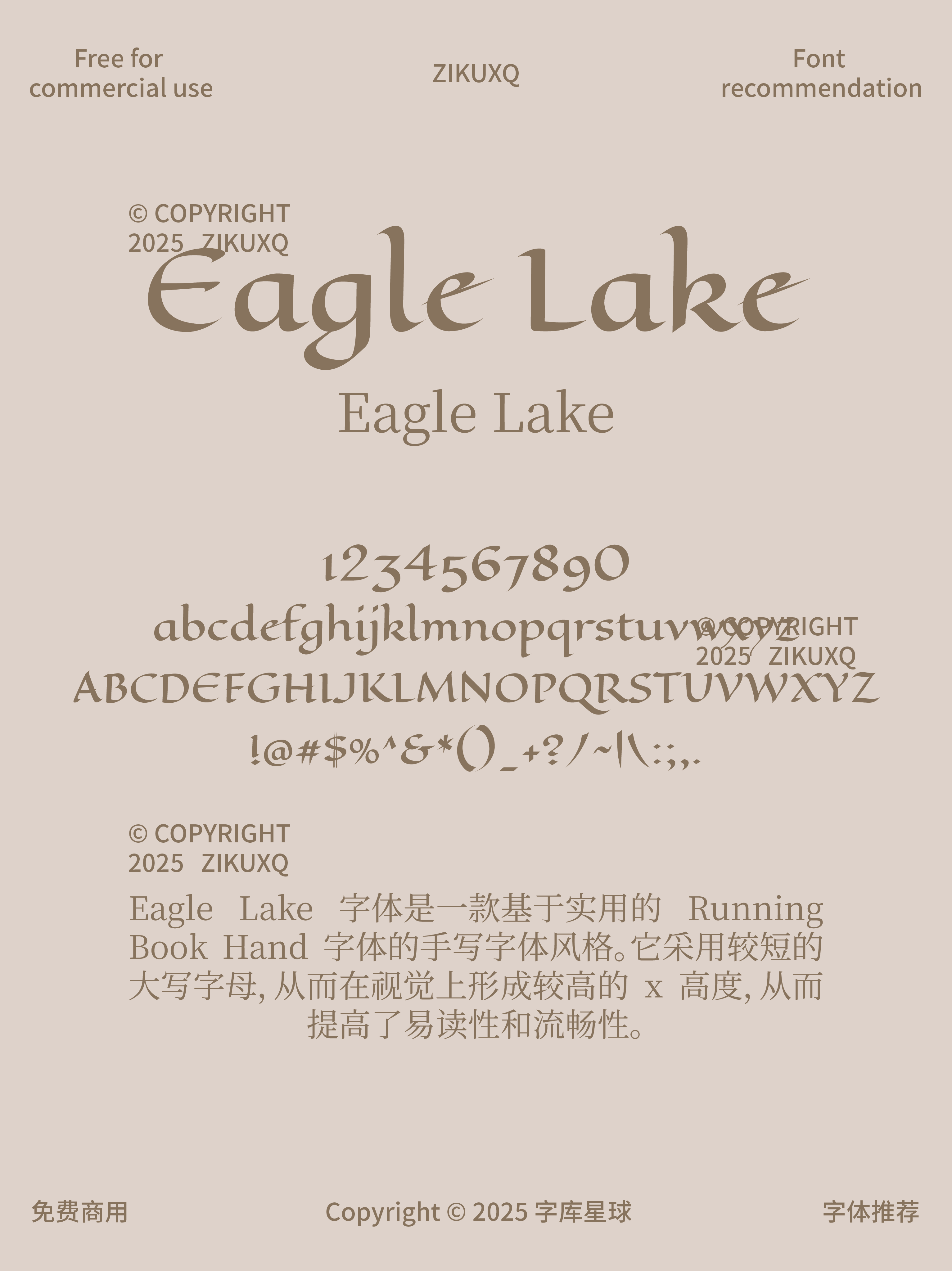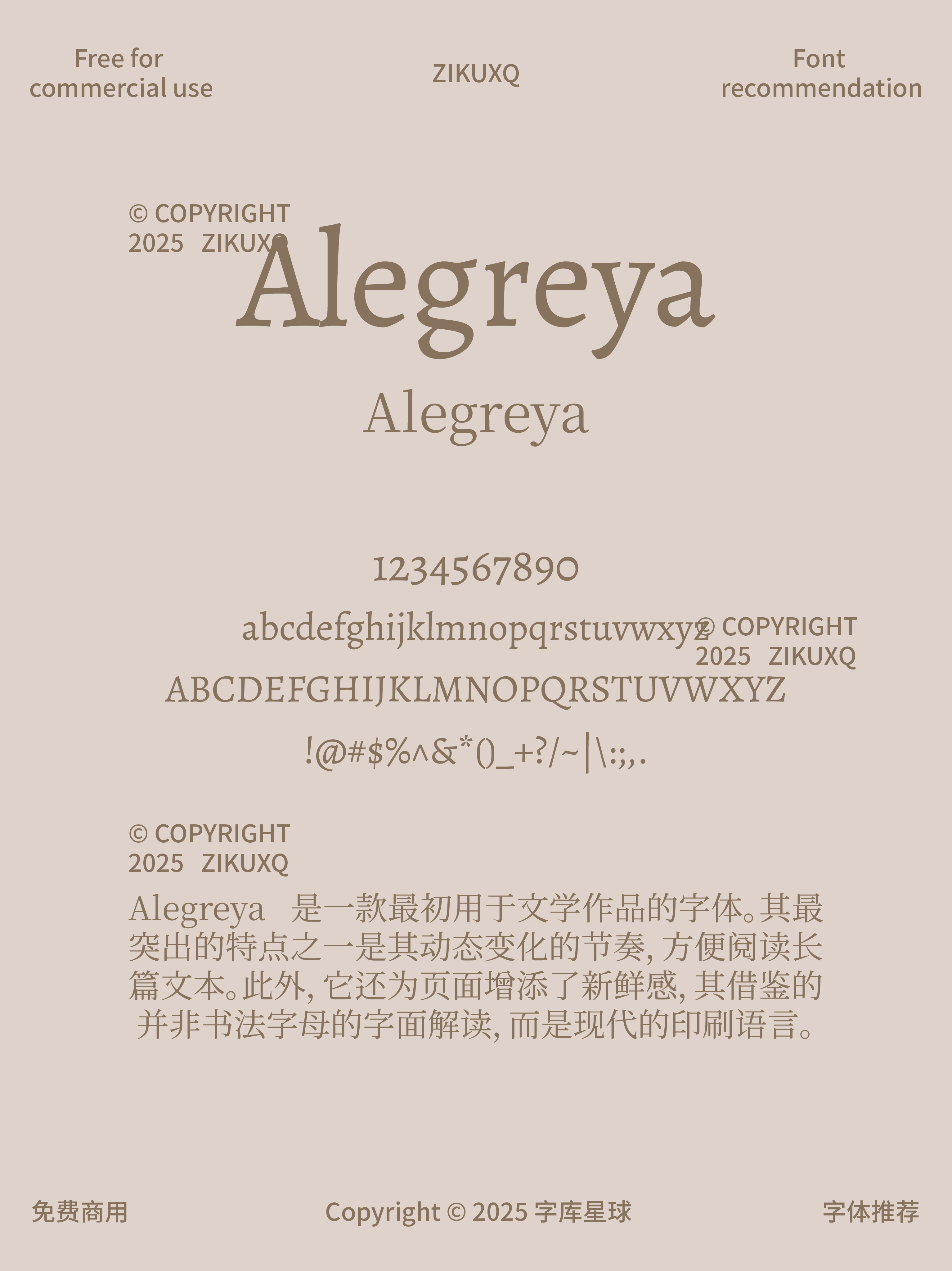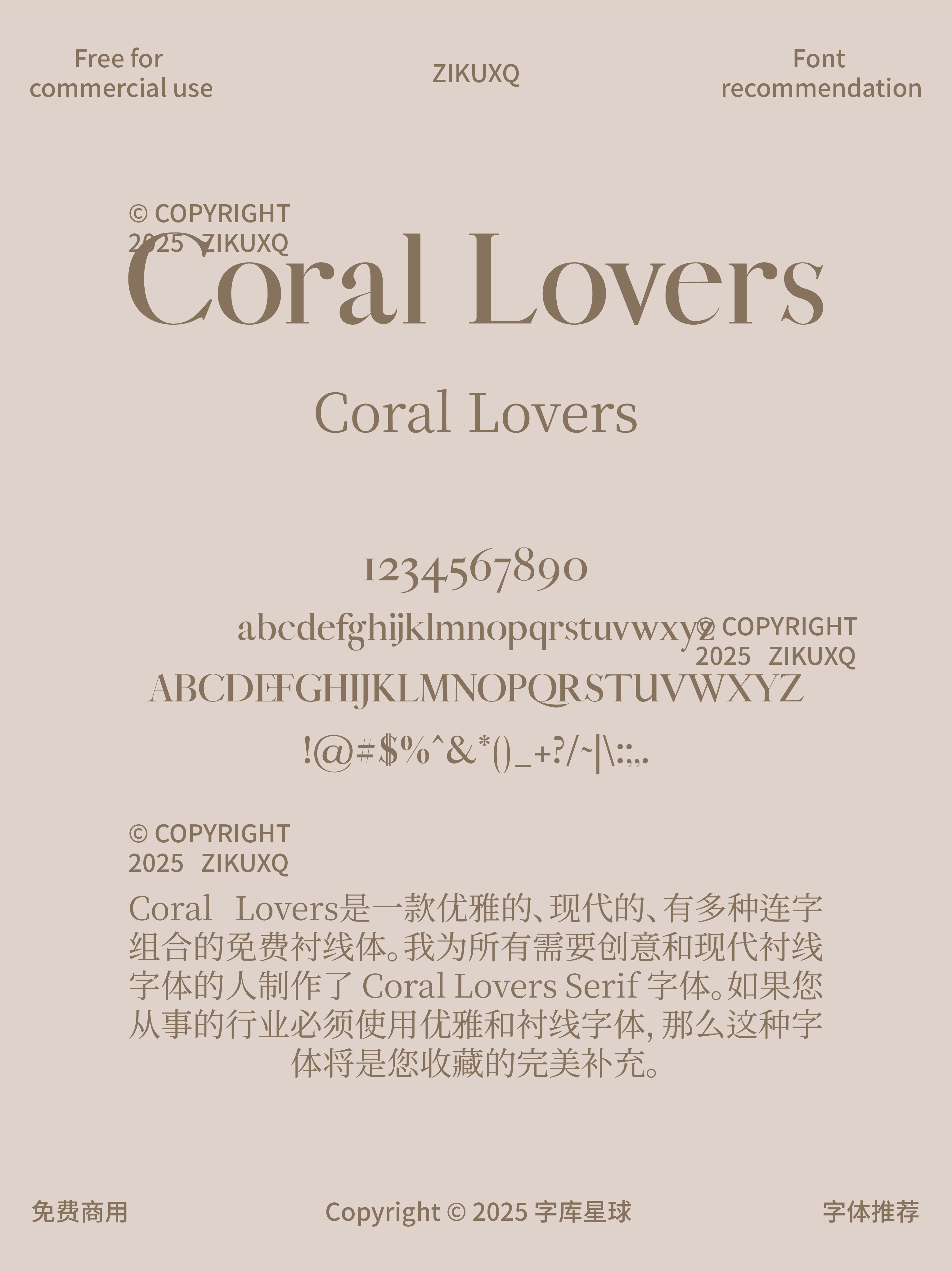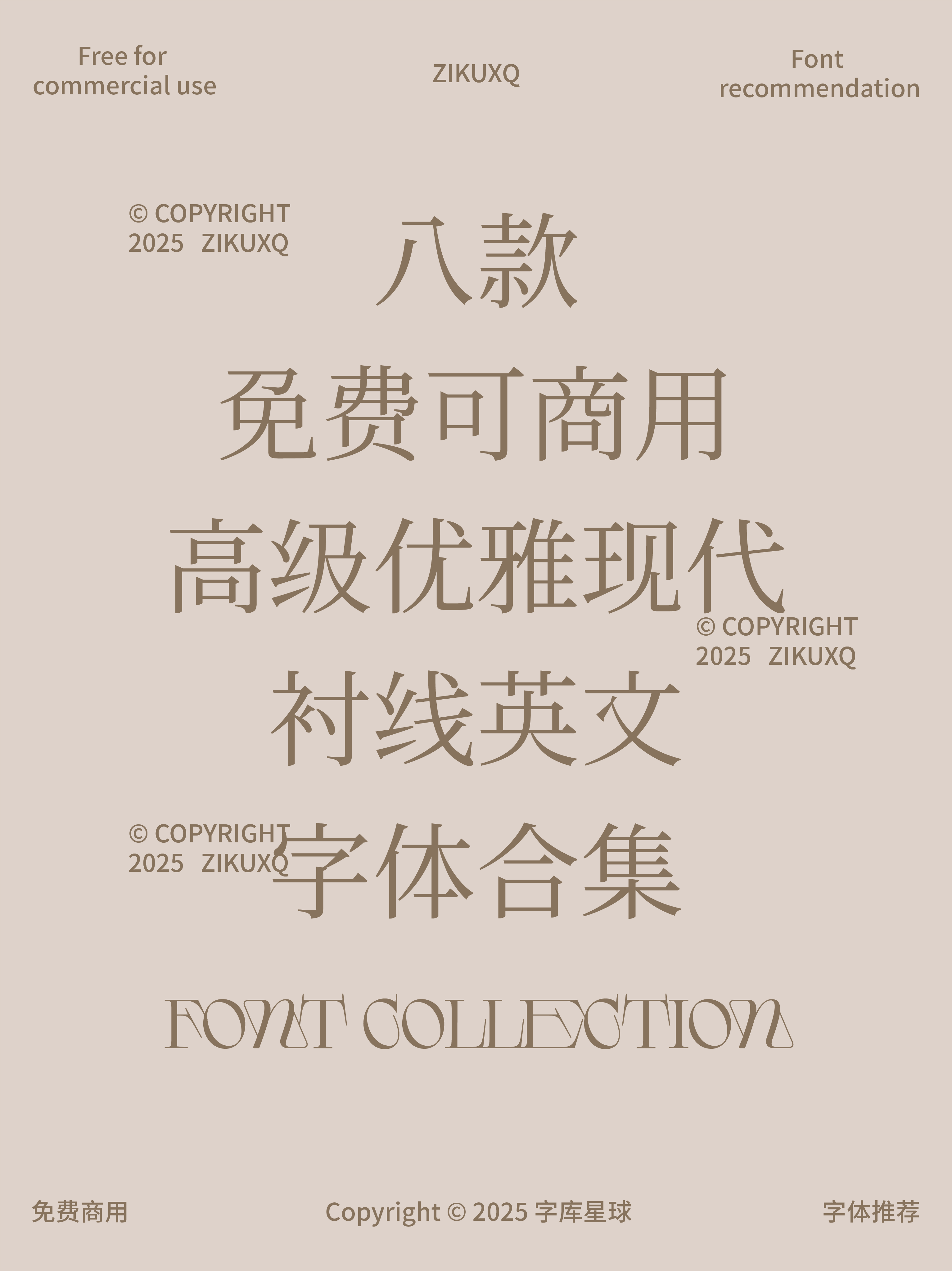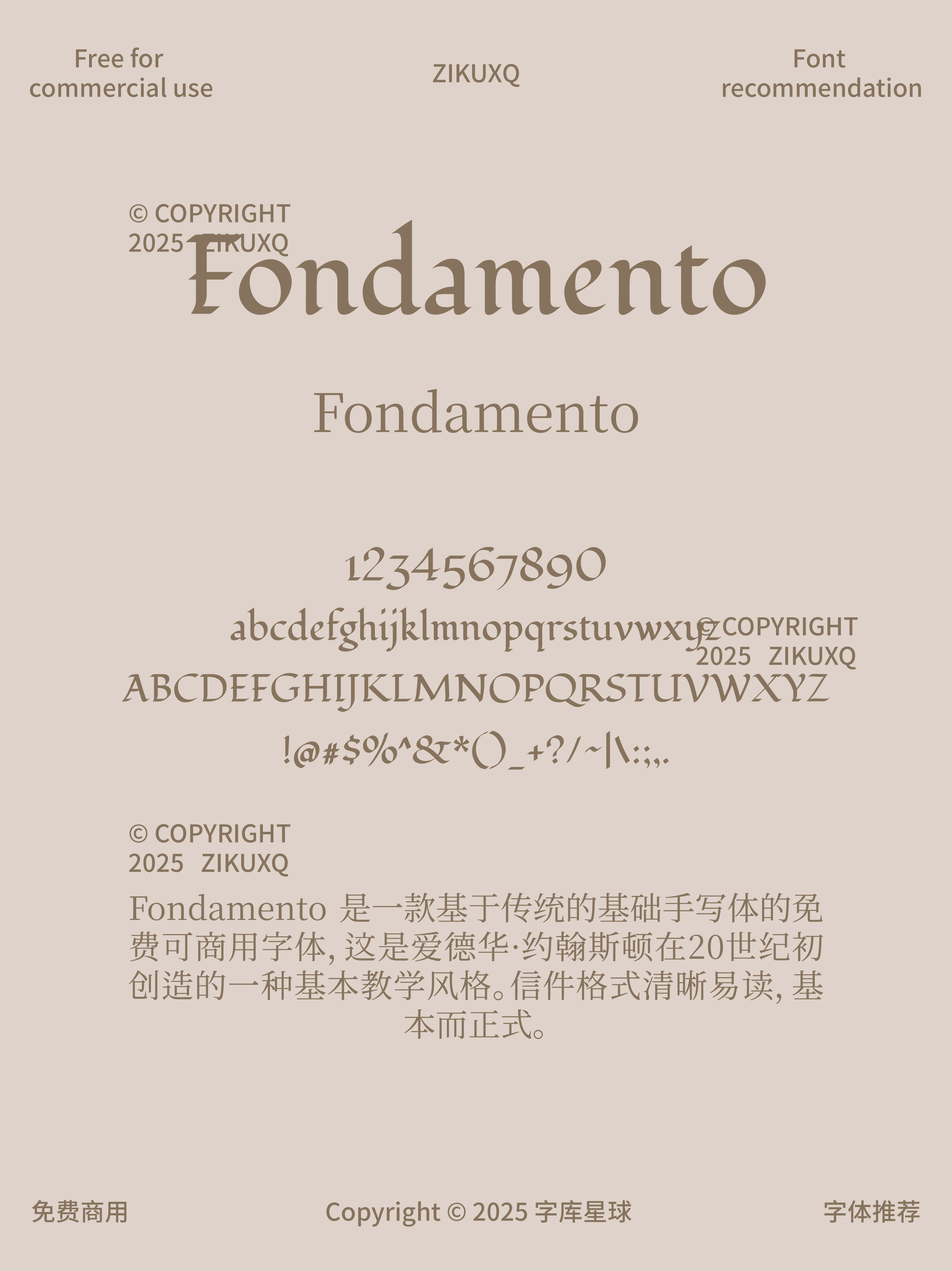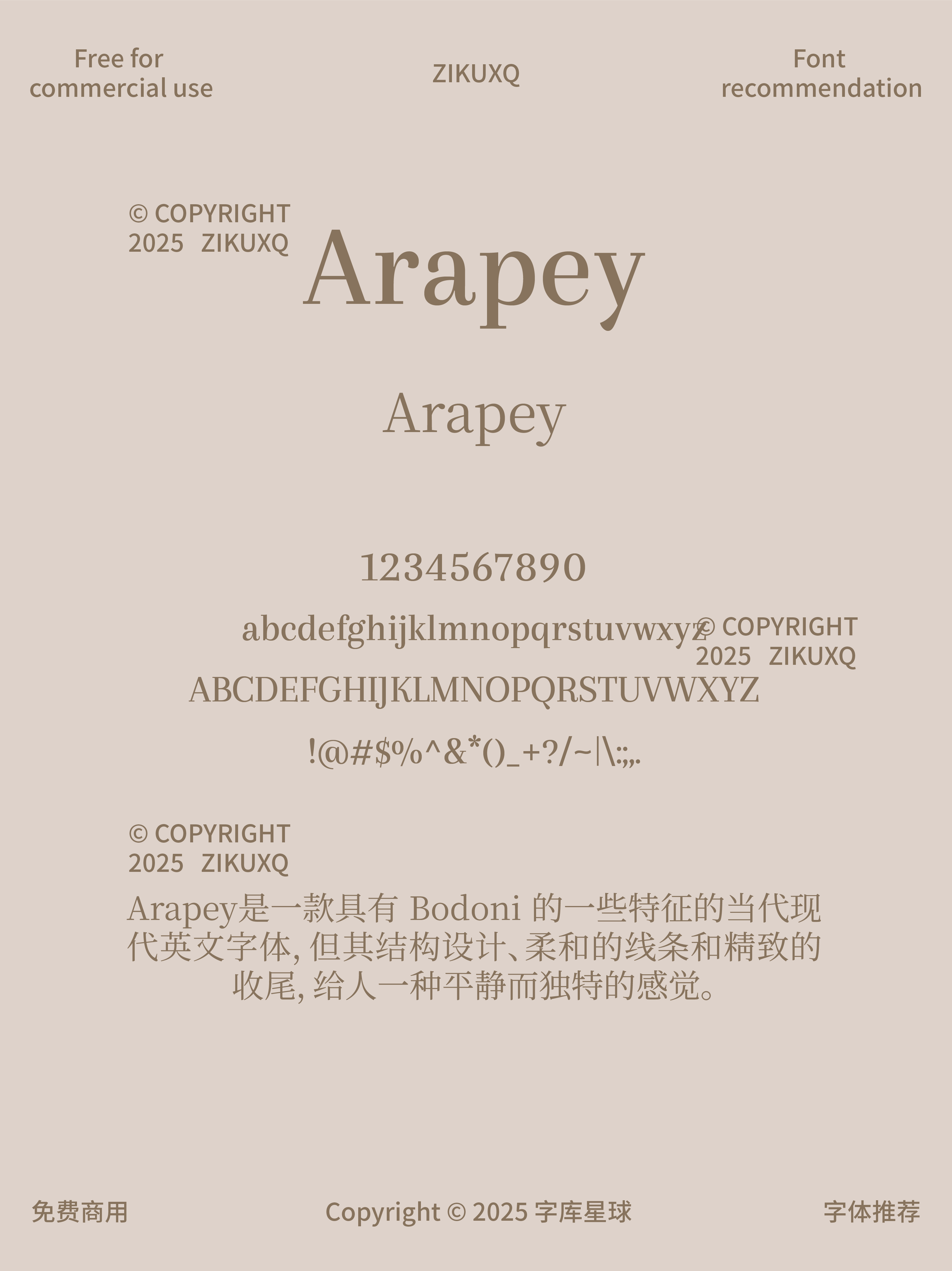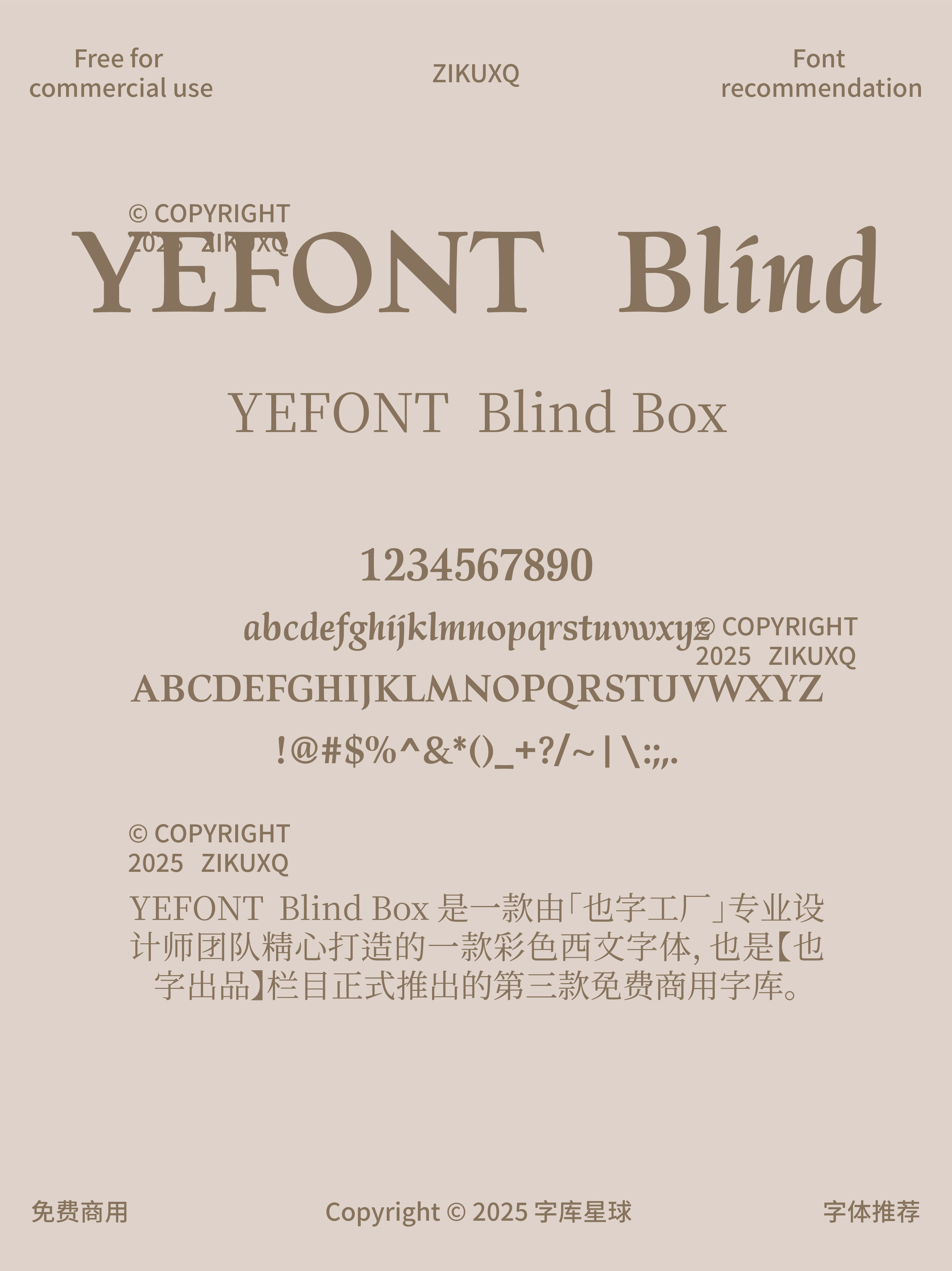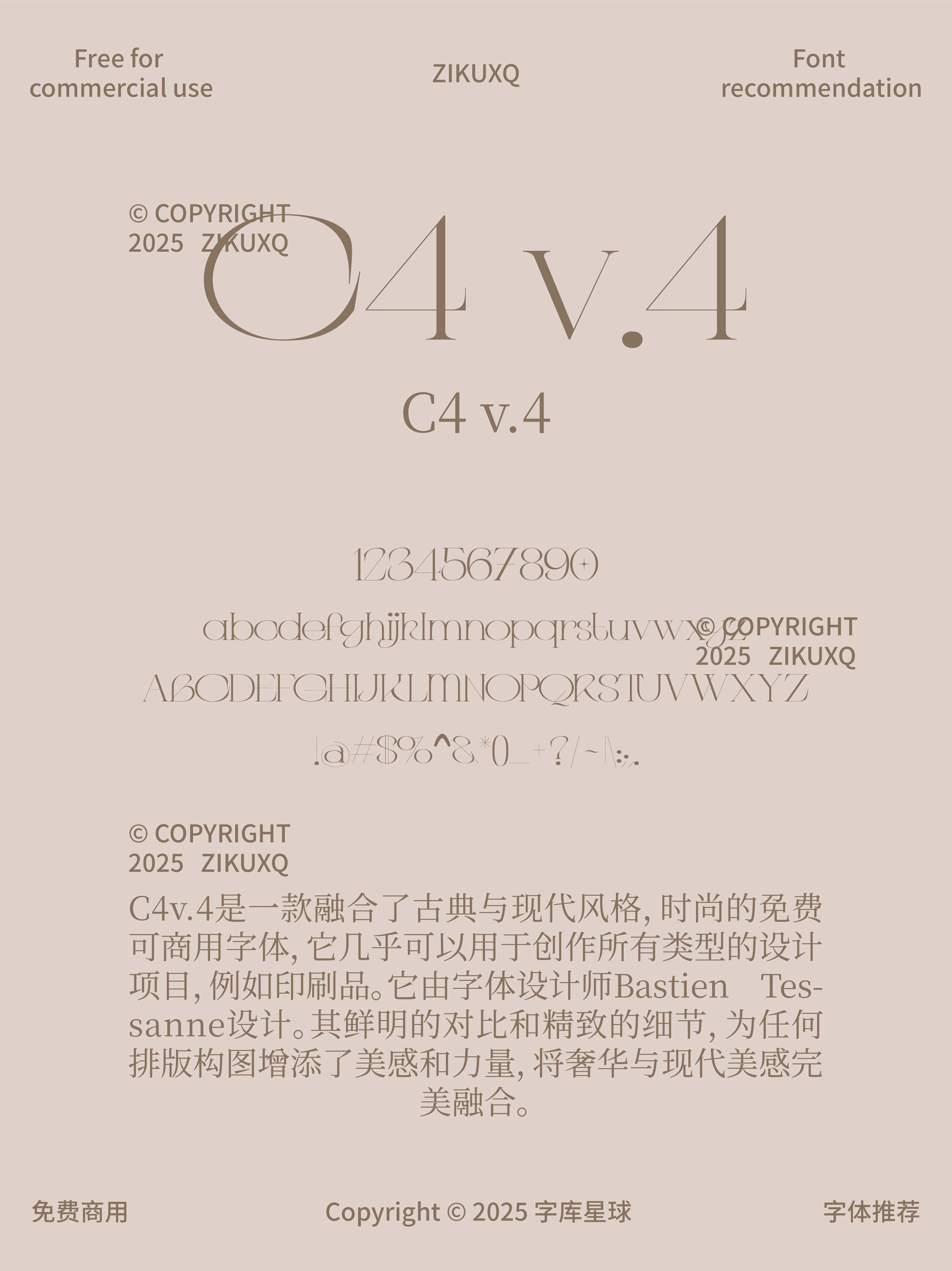
高级优雅现代衬线英文
分享八款免费可商用高级优雅现代衬线英文字体合集,颜值爆表还免费可商用,做设计时用它们,高级感瞬间拉满~
线条利落又带点柔美弧度,像精致的艺术品​,无论是海报标题还是品牌 logo,都能 hold 住场面,超有格调!轻盈又不失力量感,字母间的留白恰到好处​,搭配时尚、美妆类设计,温柔中透着高级。
小巧精致的字体,像个优雅的小精灵​,做手账装饰、文创产品设计,可爱又不失高级。